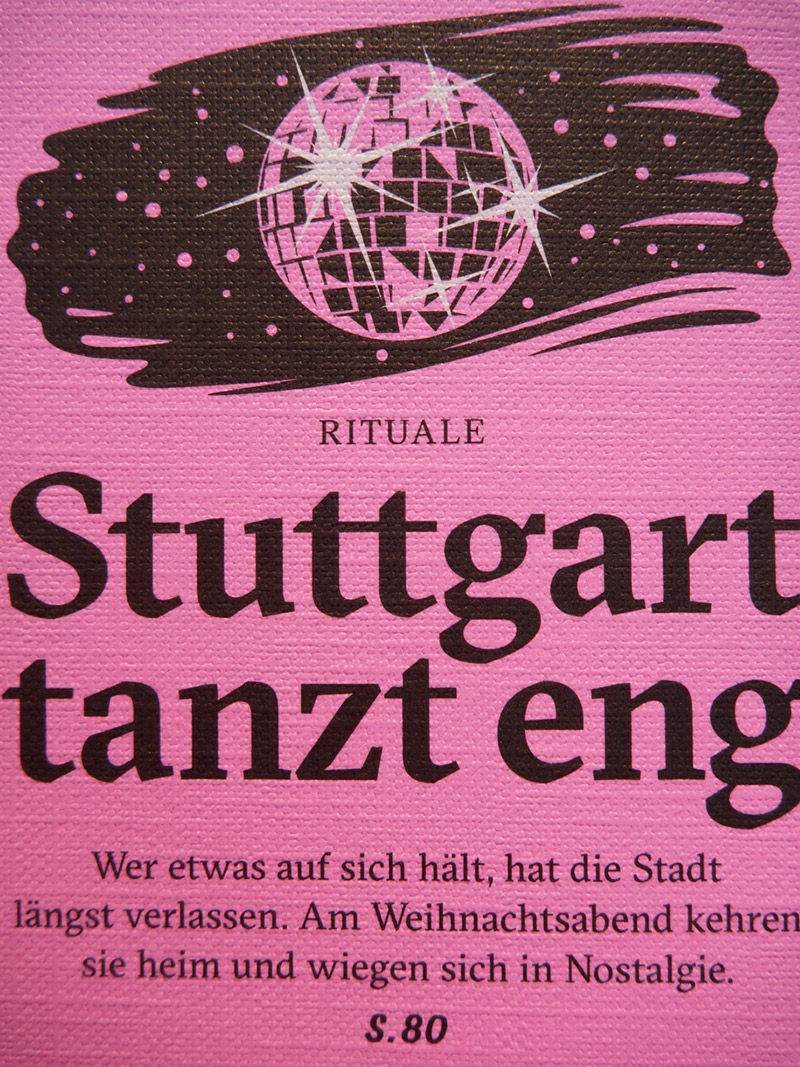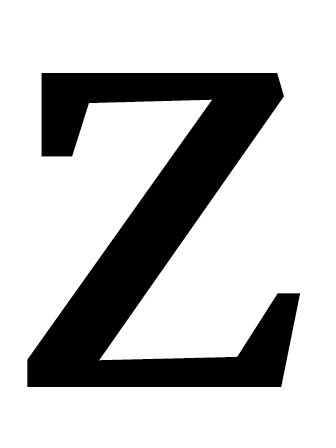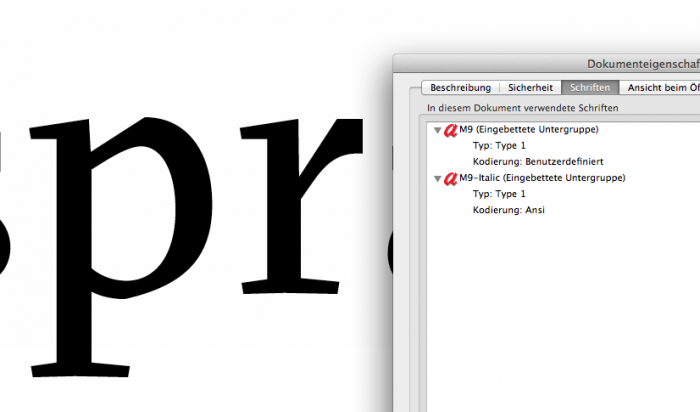
M9
Die ist aber wohl nur ganz ähnlich und nicht genau die gesuchte. :-?
Noch das "z" der M9 zum Vergleich:
In der M9 ohne Tintenfalle, in der gesuchten mit.